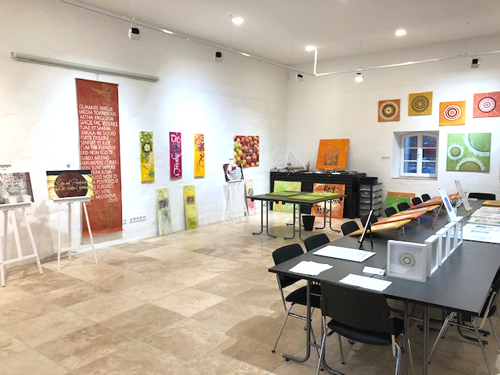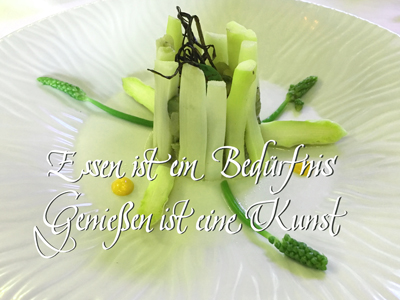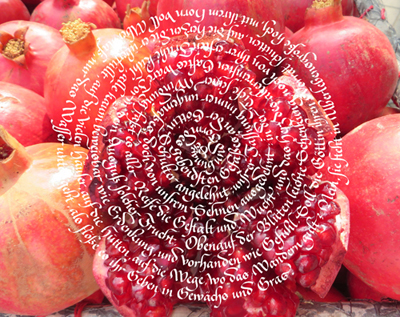
Treten Sie ein und genießen Sie einen kleinen Rundgang durch die Galerie und das Museum!
KALLIGRAFISCHE ART CULINAIRE
mit neuen Arbeiten von Katharina Pieper eröffnet. Die Schriftkünstlerin hat sich mit dem Thema
"Essen, Genießen, Versuchungen" befasst und es in vielschichtiger Weise künstlerisch umgesetzt.
Kalligrafische Originalarbeiten auf Papier und Leinwand hat sie mit Fotografien,
die zum Großteil von Dr. Irene Özbek stammen, kombiniert. So entstanden nicht nur
neue farbige Schrift-Malereien, sondern auch Drucke auf Leinwand und Acrylplatten.
Diese Ausstellung wird im Laufe der Präsentation ständig ergänzt – work in progress.
An den Tischen wird auch gearbeitet und Kurse abgehalten.
Im Gewölbekeller unter dem Galerie- und Workshopraum befindet sich das Museum für Kalligrafie und Handschrift. Hier sind Schreibwerkzeuge aller Art wie Federn, Pinsel und experimentelle Schreibinstrumente sowie Tinten, Tuschen und weitere Schreibflüssigkeiten und Beschreibstoffe zu sehen. Ein historischer Überblick über die Entwicklung unserer Schrift darf natürlich nicht fehlen. Schautafeln erklären die Herkunft unserer lateinischen Schrift und erklären den Unterschied zwischen Kalligrafie und Handschrift. An speziell installierten Schienen ist eine Dauerausstellung von Jean Larcher mit Original-Kalligrafien zu sehen, die er für sein Buch Traits de Caractère" geschrieben hat. Auch das Jean-Larcher-Archiv hat hier seinen Platz. Eine sehr lebendige und farbige Tafel zeigt Original-Briefumschläge von Jean Larcher an Katharina Pieper – alle per Post verschickt! |
Einblick in einige Vitrinen zum Thema Tinten und Schreibwerkzeuge
Eine Vitrine (re.) mit chinesischen Schreibutensilien wie diversen Pinsel, Reibetusche und -steinen, Stempel und Stempelfarben
In der linken Vitrine sind neben außereuropäischen Kalligrafien auch verschiedene Auszeichnungen für Katharina Pieper zu sehen, die sie z.B. in Indien,
den Vereinigten Arabischen Emirate, Korea oder St. Petersburg erhalten hat. Sie demonstrieren den Stellenwert der Kalligrafie in diesen Ländern.
Bei uns kann man von dieser Wertschätzung nur träumen...
Rechts ist eine Vitrine zu sehen, in der einige handschriftliche Aufzeichnungen von Jean Larcher gezeigt werden,
die während der Arbeit am Buch "Traits de Caractère" entstanden sind.
Eine komplette Vitrine ist einzig und allein dem Buchstaben K gewidmet. Katharina Pieper sammelt sein vielen Jahren K's,
die im Gut Königsbruch gleich dreifachen Sinn gefunden hat: K für Kalligrafie, Königsbruch und Katharina!
Rechts ein Blick in die Vitrine, die dem handgeschriebenen Brief gewidmet ist.